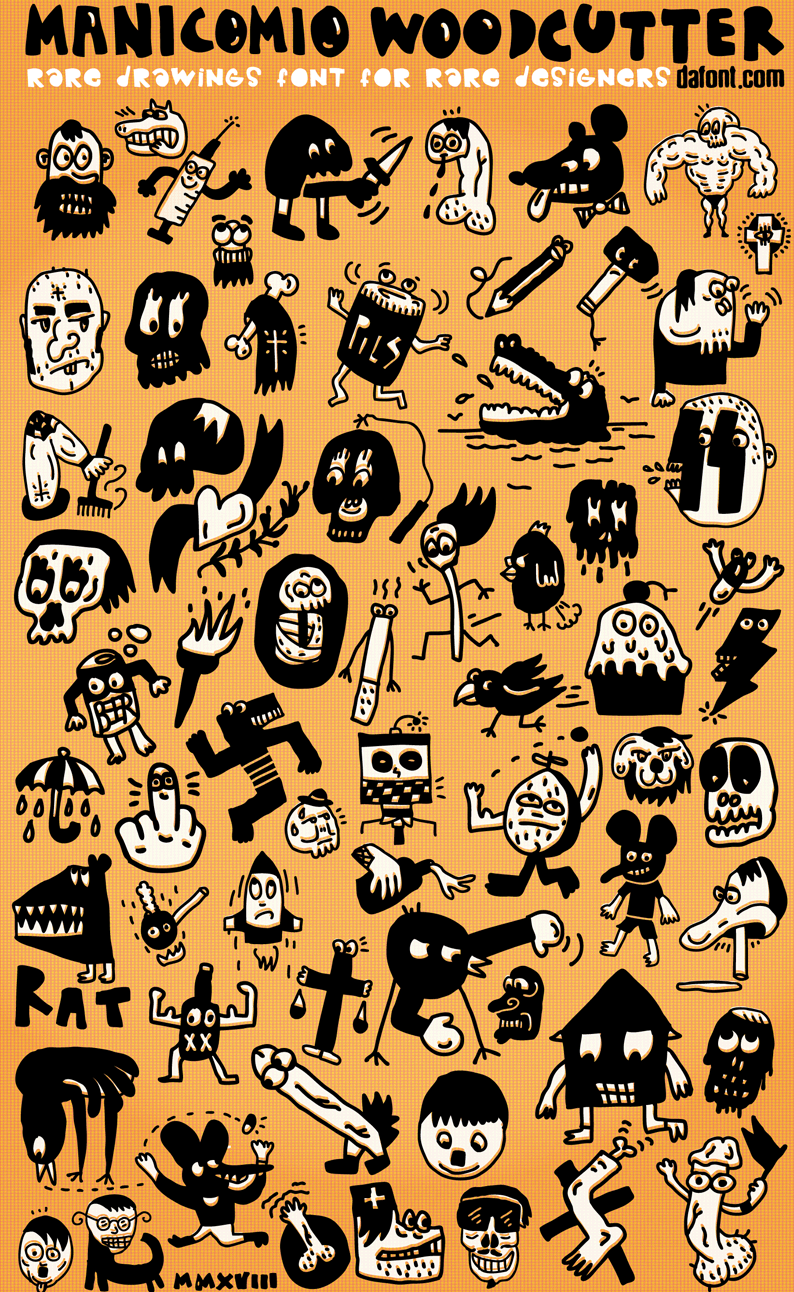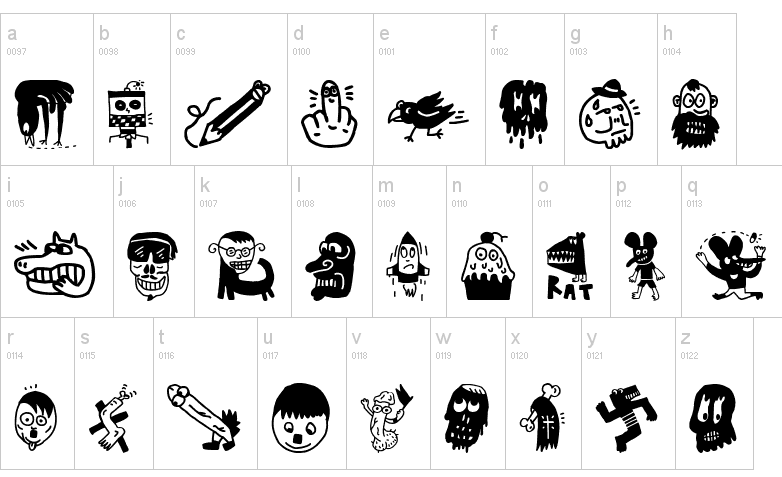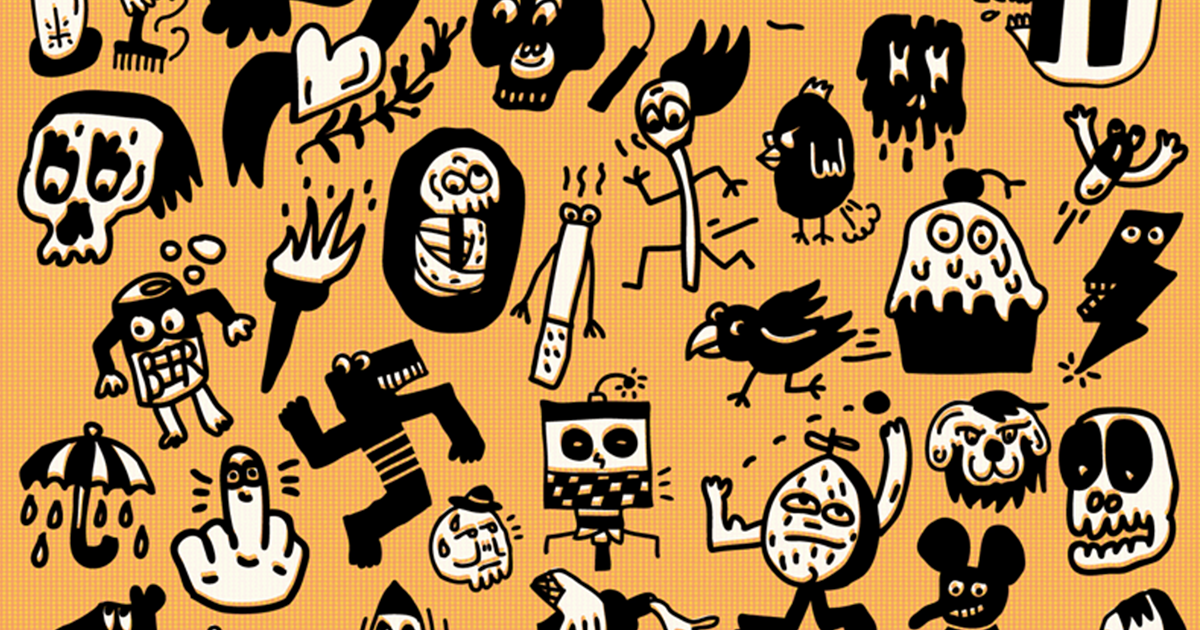
Descarga gratis la tipografía Manicomio, de Woodcutter
Este gran ilustrador comparte gratuitamente con Domestika su peculiar, hilarante y peligrosa tipografía
Seguramente has visto el trabajo de Jordi Manero, mejor conocido como Woodcutter. Ya sea por sus críticas pero divertidas ilustraciones, por alguna de sus curiosas fuentes, o tal vez por "I See Dead Fonts", el proyecto que recopila rótulos clásicos de tiendas y establecimientos en España con el fin de tener un archivo de las tipografías que se usaban en antaño.
Influenciado por el expresionismo abstracto, el arte conceptual y el gusto por el DADA, además de los cómics, los clásicos de Bruguera, García-Sevilla, Caravaggio, Basquiat, Piranessi y Bruce Nauman; estudió Bellas Artes y pintura, pero enfocado al diseño gráfico, comenzó a mezclar la ilustración con la tipografía usando su propio tipo de letra en cada una de sus piezas, por lo que pensó en crear la fuente para ahorrar tiempo de trabajo.
Posteriormente probaría adaptando dibujos pequeños, bocetos y símbolos en sus días libres. Dentro de sus creaciones, publicó una fascinante tipografía que reúne diversos personajes que bien podrían estar internados en un centro psiquiátrico animado: desde cocodrilos gritando, aves violentas, cráneos molestos, ratones medicados, cigarrillos malhumorados, hasta penes con pequeñas banderas. Un compilado que más de uno catalogaría de "enfermo", pero que resulta sumamente divertido y del que Jordi nos contó un poco:
"La tipografía empezó con el dibujo, siendo rápido, sin apenas retoque y dibujado directamente en tableta gráfica usando Photoshop. Uso un viejo HP Touchsmart TM2, una chatarra indecente, pero me sirve para el fin. Los dibujos son automáticos y algo enfermos, una vez terminados, los vectorizo con Illustrator para pasar a posicionarlos en su lugar del alfabeto y del teclado con High-Logic Font Creator, que para mí, su interfaz me parece rápida y muy sencilla. Así la tenemos calentita y recién salida del horno".